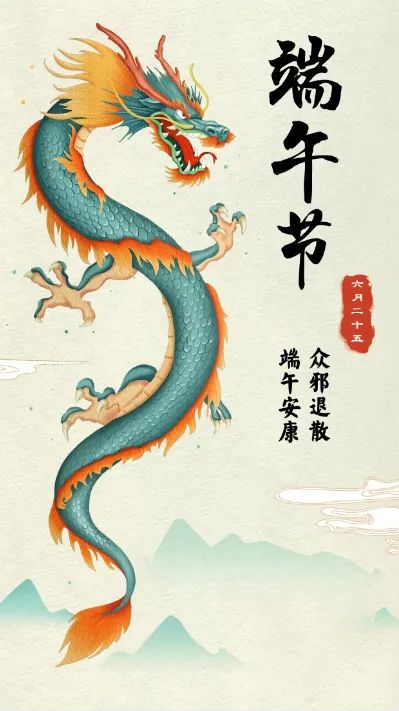
端午海报如何一秒出新意?你可以试试这些字体~
明天就是端午节了,相信设计师们应该早早就把海报做好了吧,柚子,你是不是又发晚了?nonono,节日大概的元素、排版可以提前做好,但决定画面灵魂的,还在于字体,没有选对,就少了很多内味~
所以不管你今天是已经做好了海报,还是赶紧临时抱个佛脚,都不要错过这篇选字秘籍哟!
传统书法
一提到端午节,很多人就会把它跟传统、历史结合在一起,会首选书法字体,你可以在字由上筛选“书法体”、“中国风”……
比如汉仪程行简,就有一种古今穿越的历史浑厚感。
同时跟它搭配的汉仪颜楷,也是一款超经典的书法字体。
另外其他楷体,比如偏诗意的汉仪许静行楷~
偏硬朗的汉仪劲楷~
以及字由新上的汉仪字酷堂南元行楷,都很适合用在端午海报上。
不同口味
如果每年都是传统字体,难免会没有期盼,所以要不断激发新鲜感,甜的、咸的……各来一样。